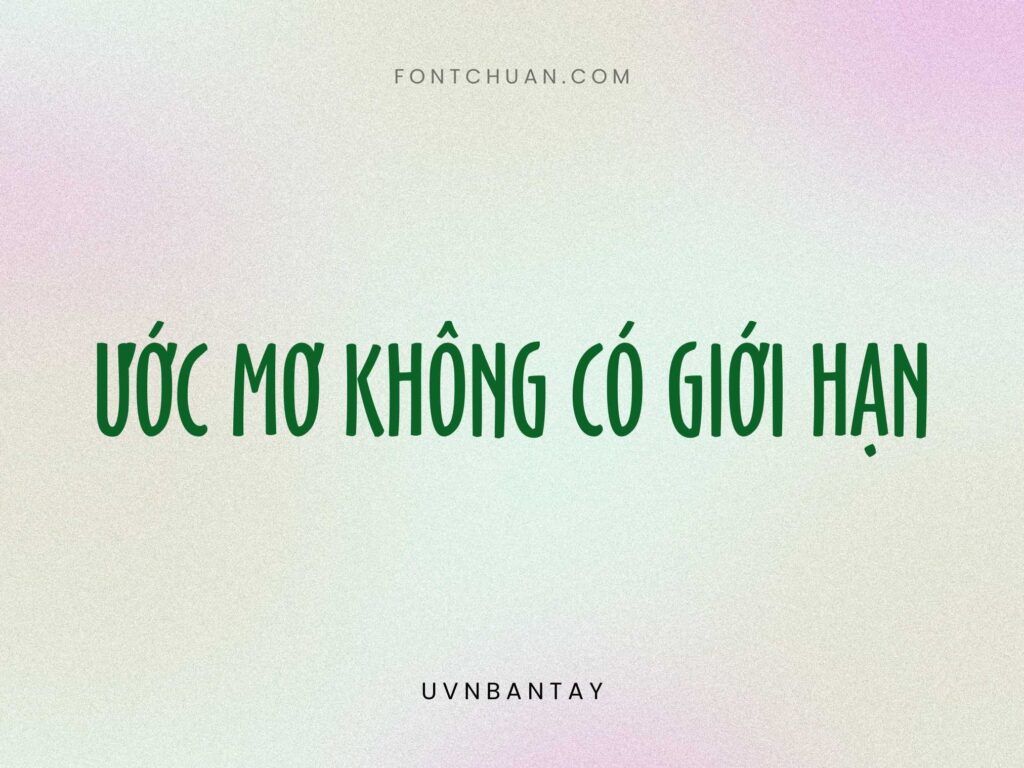
Font UVN Ban Tay Việt Hóa
UVN Bàn Tay là một phông chữ viết tay độc đáo, được thiết kế bởi Tom Trương vào năm 2001. Phông chữ này mang lại cảm giác vui nhộn và thân thiện cho các thiết kế, với các đường nét mềm mại, phồng lên như những nét vẽ bằng tay, tạo nên sự tươi vui và sáng tạo. UVN Bàn Tay hỗ trợ đầy đủ các ký tự tiếng Việt, giúp người dùng dễ dàng sử dụng trong nhiều loại dự án khác nhau.
Với thiết kế độc đáo và nghệ thuật, UVN Bàn Tay phù hợp cho các ứng dụng như thiệp mời, tiêu đề sách, thiết kế logo và các ấn phẩm nghệ thuật. Trong lĩnh vực sự kiện, phông chữ này có thể được sử dụng trong các dịp như lễ hội, lễ cưới và các sự kiện văn hóa. Ngoài ra, UVN Bàn Tay cũng rất thích hợp làm Font chữ ảnh cưới, lý tưởng để thiết kế thiệp cưới, album ảnh và các sản phẩm liên quan đến đám cưới, mang lại cảm giác ấm áp, tinh tế và đầy tình cảm. Phông chữ này cũng phù hợp cho các ngành nghề như thiết kế đồ họa, nghệ thuật trang trí và xuất bản.